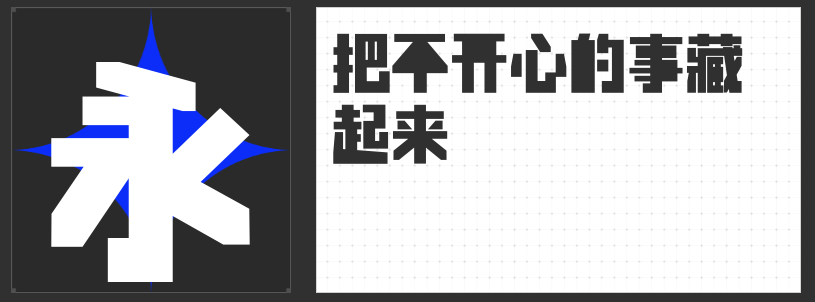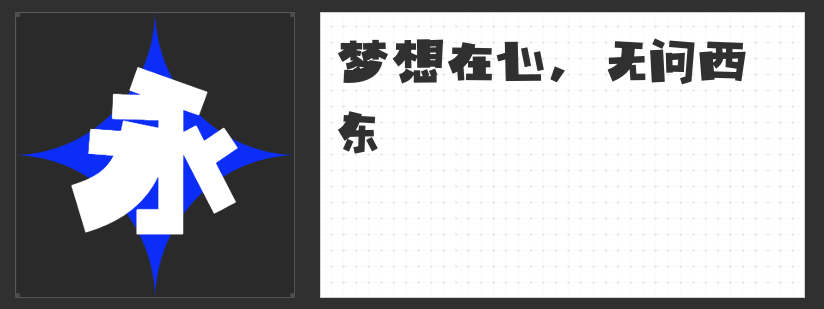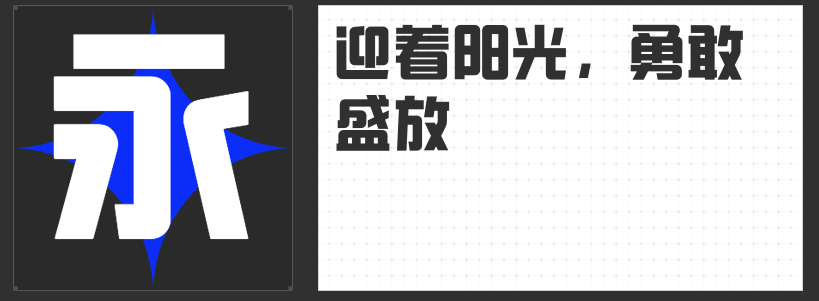
创意无界:四款突破常规的字体设计力作
在视觉设计的浩瀚宇宙中,字体不仅是信息传递的载体,更是情感与风格的塑造者。今日推荐四款独具匠心的创意字体,它们以非凡的创意与精湛的工艺,为设计领域注入无限活力。
这款现代创意黑体,以其厚重的字型与开放性的设计语言,挑战着传统黑体的界限。笔画间的不均等粗细与梯形分布,赋予文字以动态美感,硬朗而不失灵动,是追求现代文艺风格设计的理想之选。
二、创客贴综艺体粗体
在刚硬的黑体基础上,融入柔和的弧度转折,创客贴综艺体粗体以其中宫开阔的设计,展现出既稳重又不失亲和力的独特气质。它巧妙地平衡了力量与柔美,适用于需要营造温馨氛围的设计场景。
这款艺术字体,以多变字面与灵活结构,模拟出手写般的自然韵味。笔画简约而不失变化,左粗右细的对比,加之撇画的曲线元素,使得整体既具视觉冲击力,又不失文字的识别性,是追求个性与创意表达的不二之选。
四、喵字渐冻体
一款承载着社会责任与人文关怀的定制字体。它以渐冻症患者的视角出发,通过模拟疾病特征的设计,让每一笔每一划都诉说着患者的坚韧与渴望。喵字渐冻体不仅是一款艺术字体,更是一次对社会意识的深刻唤醒,鼓励人们关注罕见病群体,共同推动医学进步。
这四款字体,每一款都是对传统字体的创新突破,它们以各自独特的方式,丰富着设计的语言,激发着创意的火花。在设计的征途中,选择它们,即是选择了一段探索无限可能的旅程。